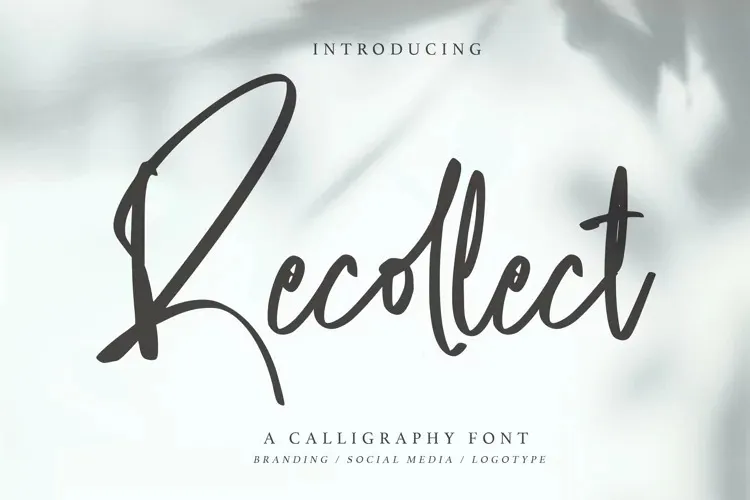
Recollect Font é uma beleza tipográfica baseada em escrita moderna com um aspecto de escrita natural. Esta fonte tem um caráter extremamente versátil e se encaixa em uma ampla variedade de projetos, elevando-os a níveis altos. Com Recollect Font, você pode explorar suas ideias criativas favoritas e notar como ela as torna realmente vivas e reais. Seja para cartazes urbanos, letras em livros ou websites elegantes, esta fonte traz um toque especial aos seus projetos. Adicione a Recollect Font à sua coleção de recursos gráficos e admire o impacto que ela pode fazer nos seus designs!